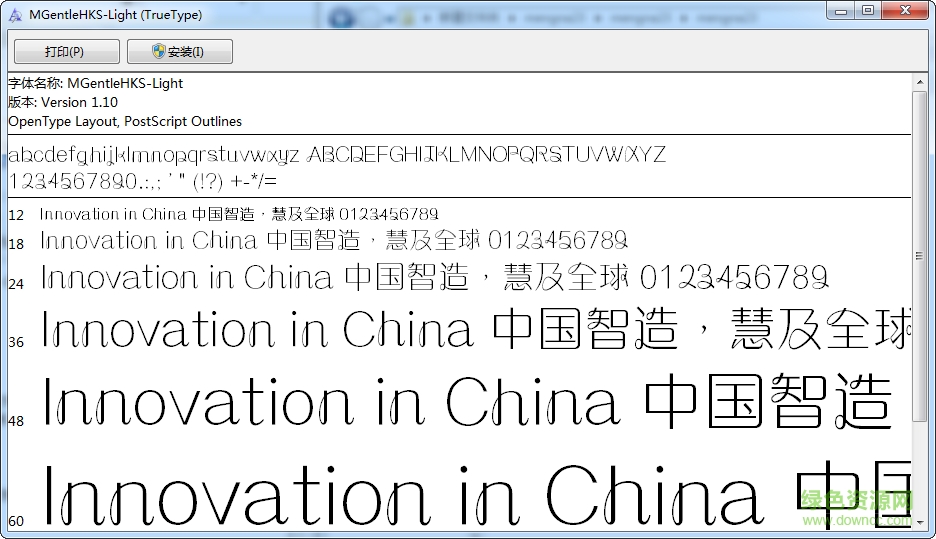
蒙納簡纖蘭字體是一款極具青春活潑氣息的方正字體,字形圓潤端莊,粗細適中,適用于各大企業(yè)的產(chǎn)品設計以及少兒圖書出版設計,有需要的朋友們趕緊來綠色資源網(wǎng)站下載吧!
面向港澳臺地區(qū)使用的字體,該字體以商用為主,字形端正大方,整體效果非常不錯,但唯一的缺點就是可以有點簡體字不能正常顯示??梢詰糜趶V告設計、平面設計、印刷包裝、報紙雜志等行業(yè),使用時請選擇“MGentle hks xbold”即可,喜歡的用戶可免費下載收藏。